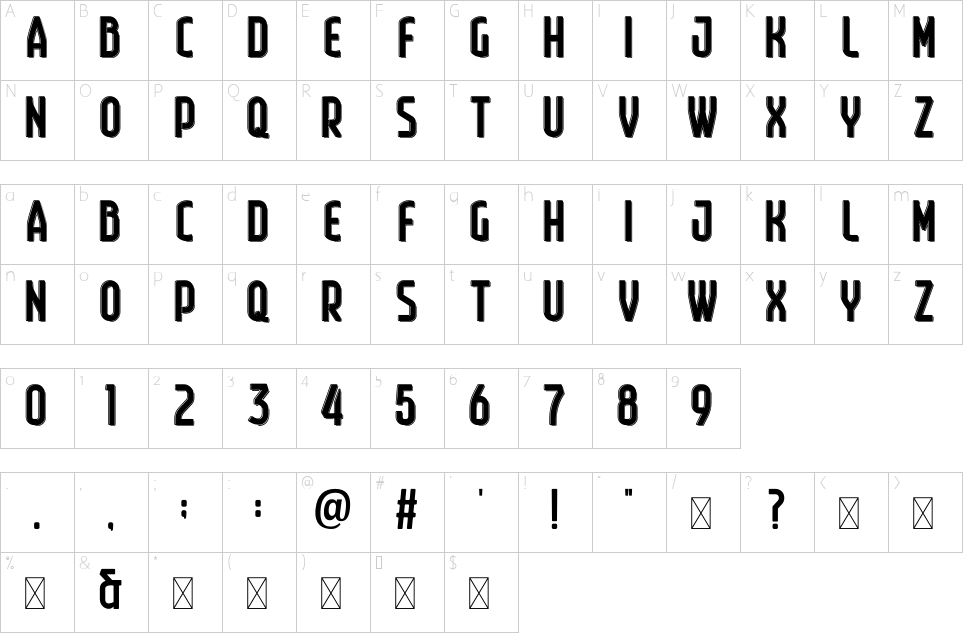
Azzurri Calcio é uma fonte desenhada pela Trequartista Studio, que se tornou uma opção popular para designers e gráficos digitais. Suas linhas elegantes e harmoniosas tornam Azzurri Calcio um recurso atraente para aplicar em projetos digitais variados, do design gráfico ao design web. Seus detalhes cuidadosos e proporções perfeitas garantem um resultado que se destaca, sem ser exagerado. Com o download de mais de 595 vezes, Azzurri Calcio é uma escolha popular para quem busca uma fonte clara e eficaz para seus trabalhos. Para quem deseja dar um toque único ao seu projeto, Azzurri Calcio oferece a oportunidade de fazer isso de uma maneira que seja elegante e acessível. Seja você um designer profissional ou um iniciante, a Azzurri Calcio é uma ótima escolha para quem valoriza a qualidade e a funcionalidade em uma fonte.